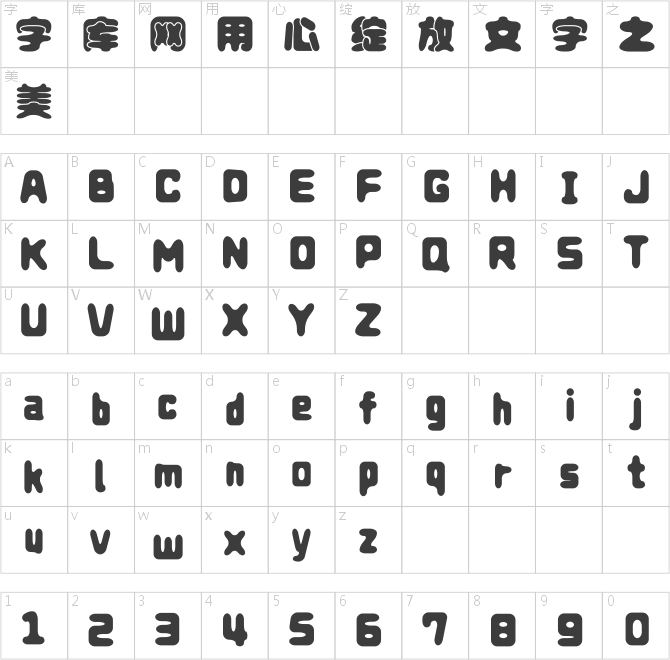
方正字跡-三余肥光體 詳情頁
字體名稱: 方正字跡-三余
方正字跡-三余肥光體
三余肥光體是一款萌胖可愛、柔軟慵懶、稚趣十足的卡通類型美術字,字體負空間極小,整體飽滿圓潤,如同QQ糖/嬰兒般柔軟且富有彈性的筆劃設定,融入部分筆劃重疊的特征,營造出萌胖稚趣的氛圍。設計之初想把肥光體設計成一款萌胖、柔軟、可愛的字體,所以在筆劃設定時,加入圓潤粗厚的筆畫特點,通過控制曲線線條的張力弧度,壓縮字面負空間,部分筆劃做重疊處理,在易識別的情況下,筆畫間的靈活搭配更突顯字體的柔軟稚趣。 適用于海報招貼,漫畫繪本、包裝產品等周邊領域。